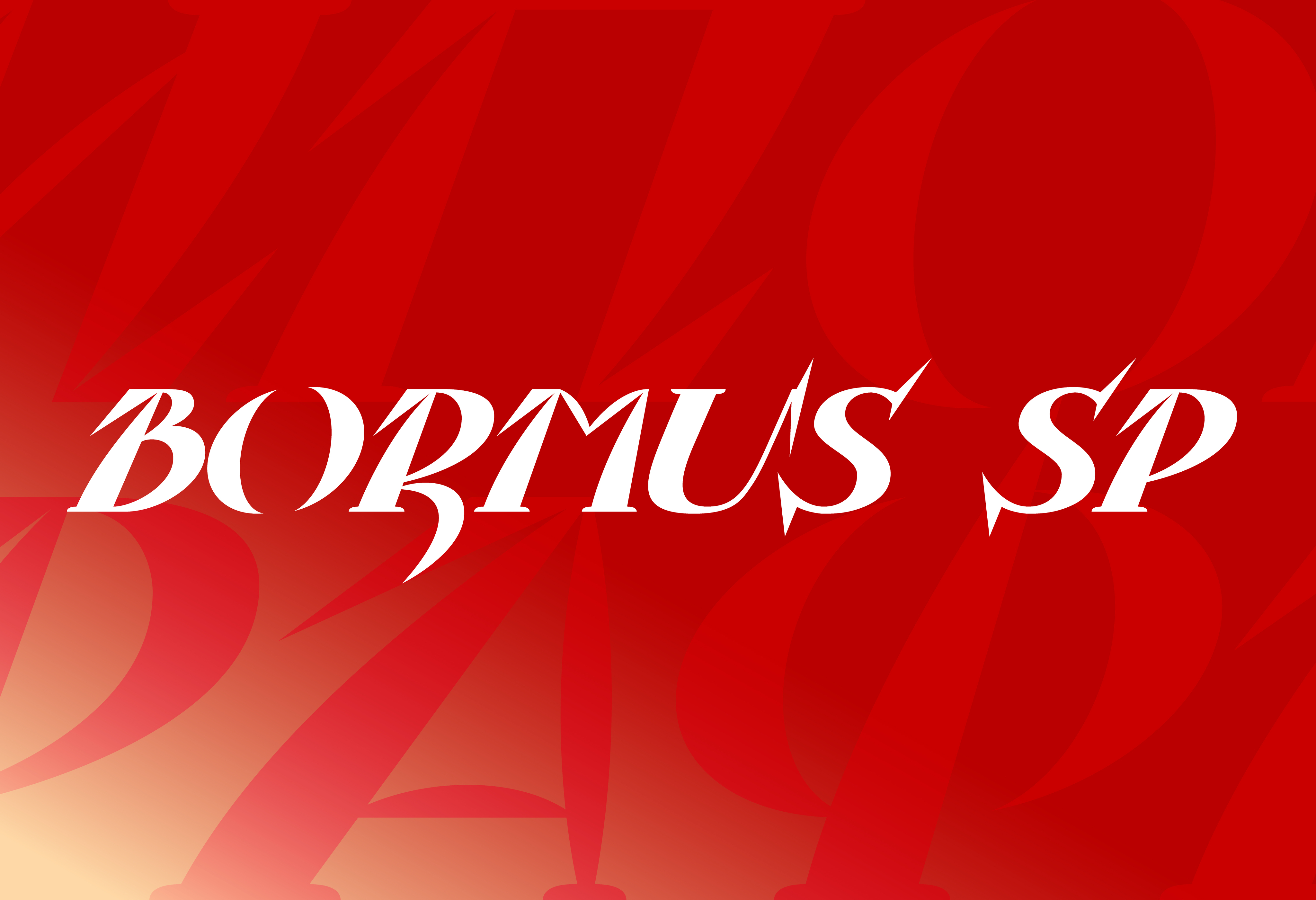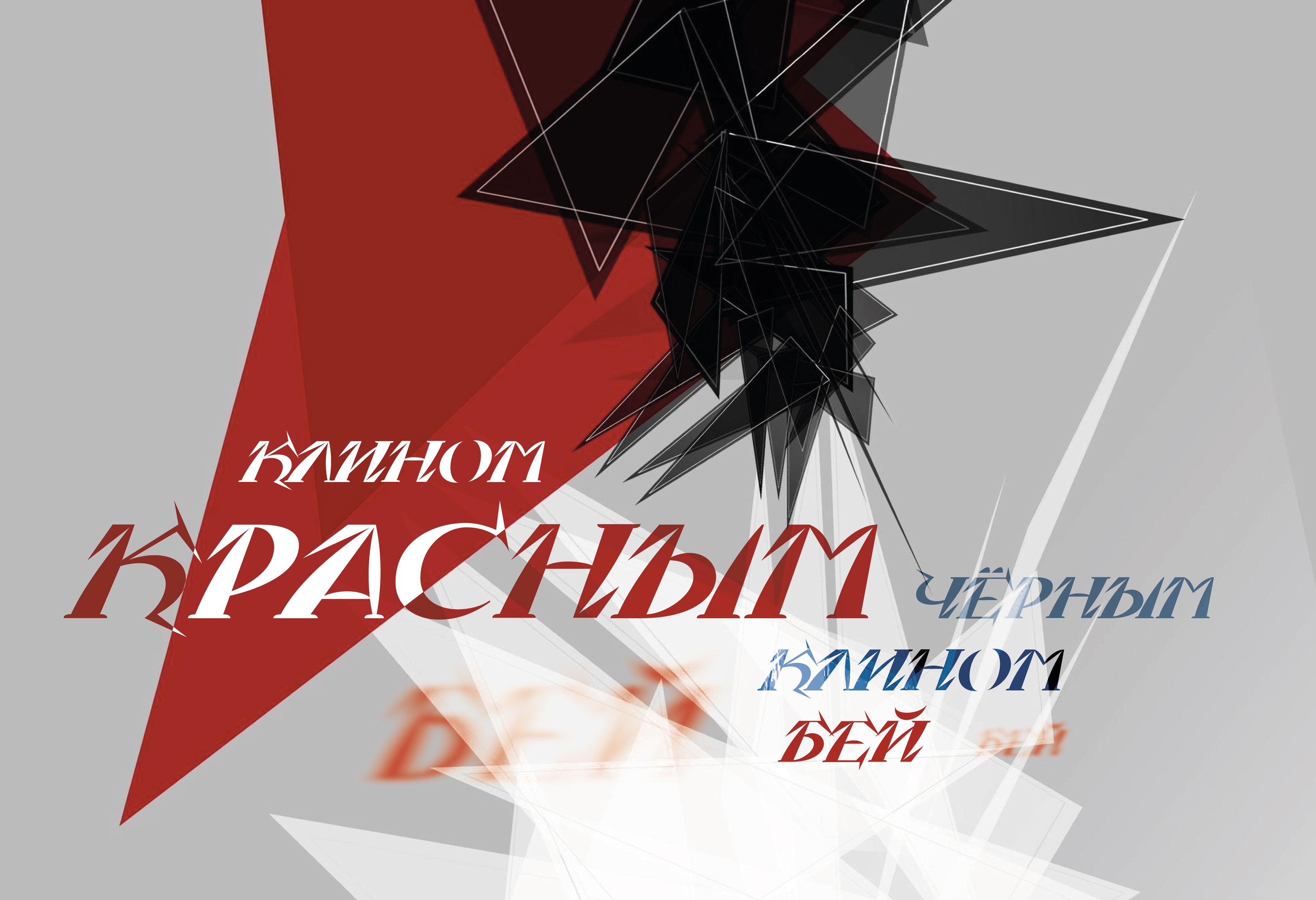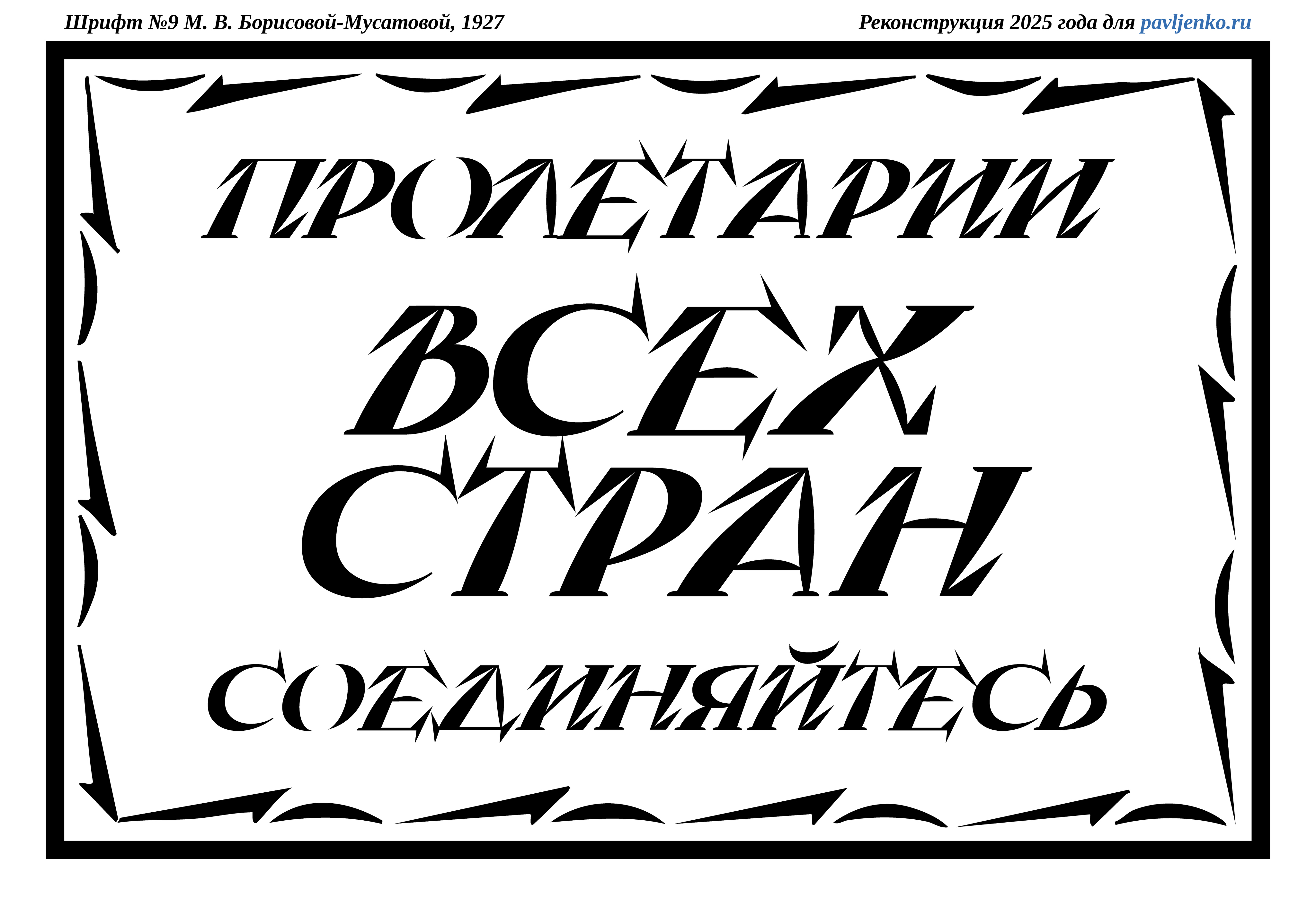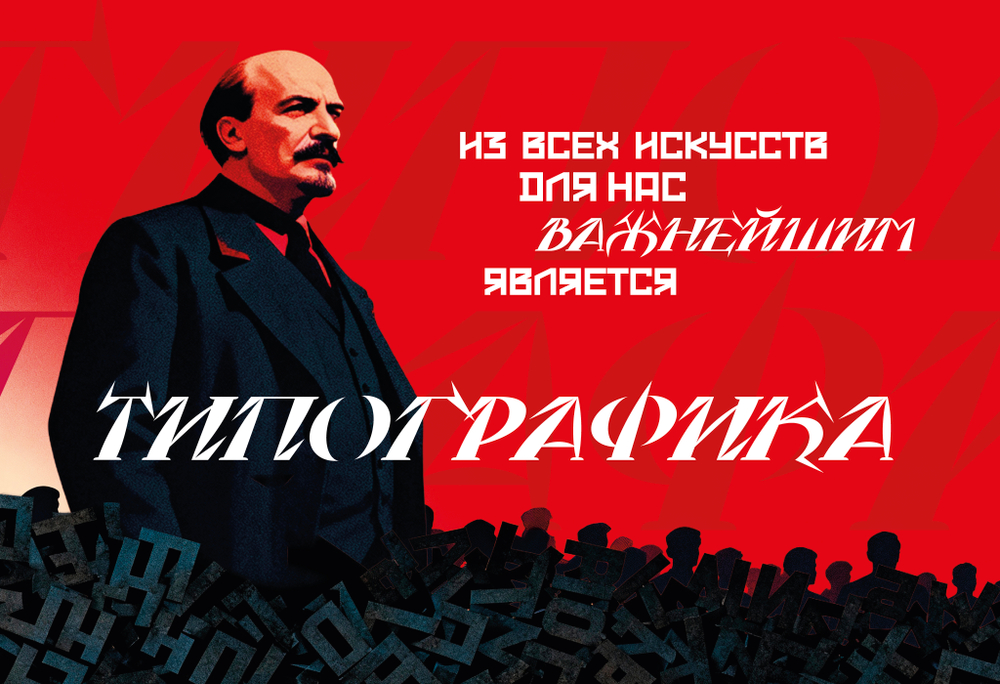
Шрифт Бормус
Bormus — плакатный шрифт по мотивам студенческого проекта М. В. Борисовой-Мусатовой 1927 года. Уверенный наклон, контрастные штрихи и заострённые окончания собираются в напряжённый, стремительный силуэт. Ритм строки намеренно неровный, пластика знаков разная — надпись выделяется даже в плотной графике. Его территория — заголовок, логотип, плакат и выставочная графика с авангардным нервом. В комплекте — полная версия STAR и лицензия.
Акцидентный шрифт